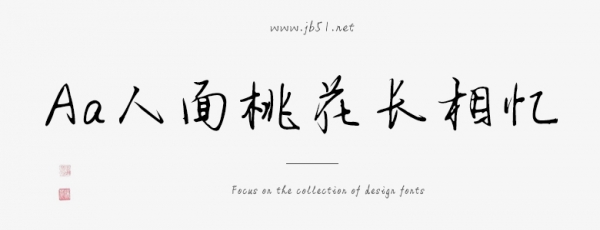
Aa人面桃花長相憶是一款不錯的藝術(shù)字體,由Aa字庫出品,字體筆觸纖細(xì),書寫流暢 ,具有很好的視覺感,適合應(yīng)用于藝術(shù)設(shè)計(jì)、平面宣傳設(shè)計(jì)、網(wǎng)頁設(shè)計(jì),書法字帖等領(lǐng)域,需要的朋友可以前來本站下載。